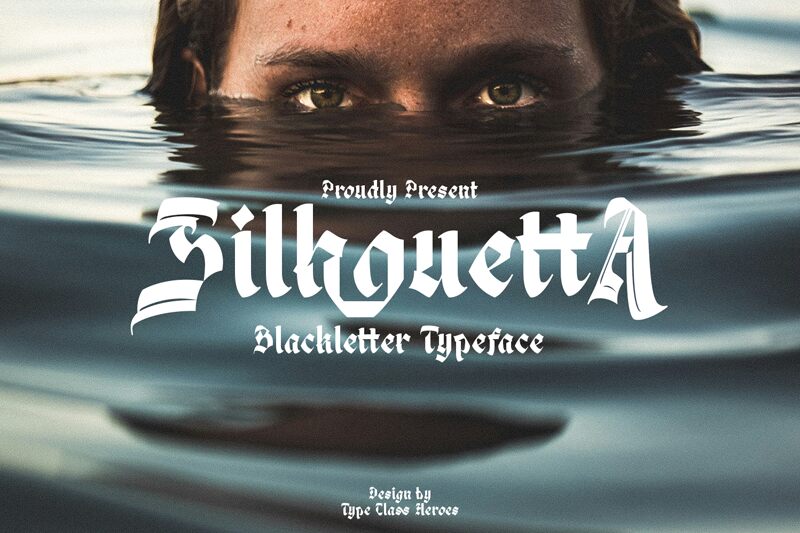
Silhouetta, de Suandana Ipandemade, é uma tipografia gótica moderna e gratuita com um toque blackletter bem definido. As letras parecem talhadas com traços amplos e angulosos, com acentos afiados em forma de diamante e curvas profundas em cunha que conferem ao estilo um ritmo cerimonial e levemente severo, sem perder a sua elegância contemporânea.
Esta fonte gratuita é ideal para branding de bebidas espirituosas e café, títulos de cartazes, capas de álbuns, editoriais de moda e cartões de título onde se procura um carácter gótico sem aquele ar medieval empoeirado. Também funciona muito bem em monogramas e textos curtos, pois as junções pontiagudas e as curvas esculpidas fazem com que até mesmo poucas letras pareçam deliberadas e dramáticas.